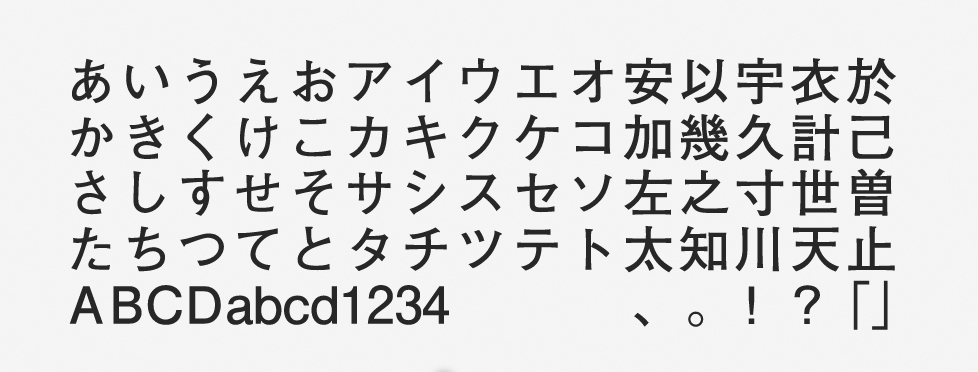
「太ゴB101」について
太ゴB101は、活字書体のデザインを忠実に引き継ぐゴシック体です。写植の時代に広く活用され、リュウミンL-KLや中ゴシックBBBに次ぐ「基本7書体」の1つとして、1991年にフォント化されました。DTPが一般化してからもオーソドックスなゴシック体として普及し、多くの場面でデザイナーに使用されています。
「太ゴB101」の特徴
太ゴB101の文字のデザインでは、縦画に筆を意識した「打ち込み」と呼ばれるアクセントが加えられています。自然に読みやすい抑揚を持たせつつ、弱く見えがちな先端はやや太くするなどの工夫も盛り込まれたフォントです。
この設計により、小さなサイズではくっきりと見え、大きなサイズでは力強く見せることができます。出版物の本文の書体から広告のキャッチコピーまでさまざまな目的で活用でき、広い範囲でオーソドックスに使える汎用性が魅力です。
長年愛用している定番フォントの1つで、似た性格を持つ中ゴシックBBBと組み合わせると、絶妙な抑揚のレイアウトを実現できます。好き・嫌いを感じさせないフォントと言えるでしょう。今回の作例は、スッキリしたイラストも使いながら、ビジュアル要素と文字の相互関係でのスムーズな訴求を狙ってデザインしています。